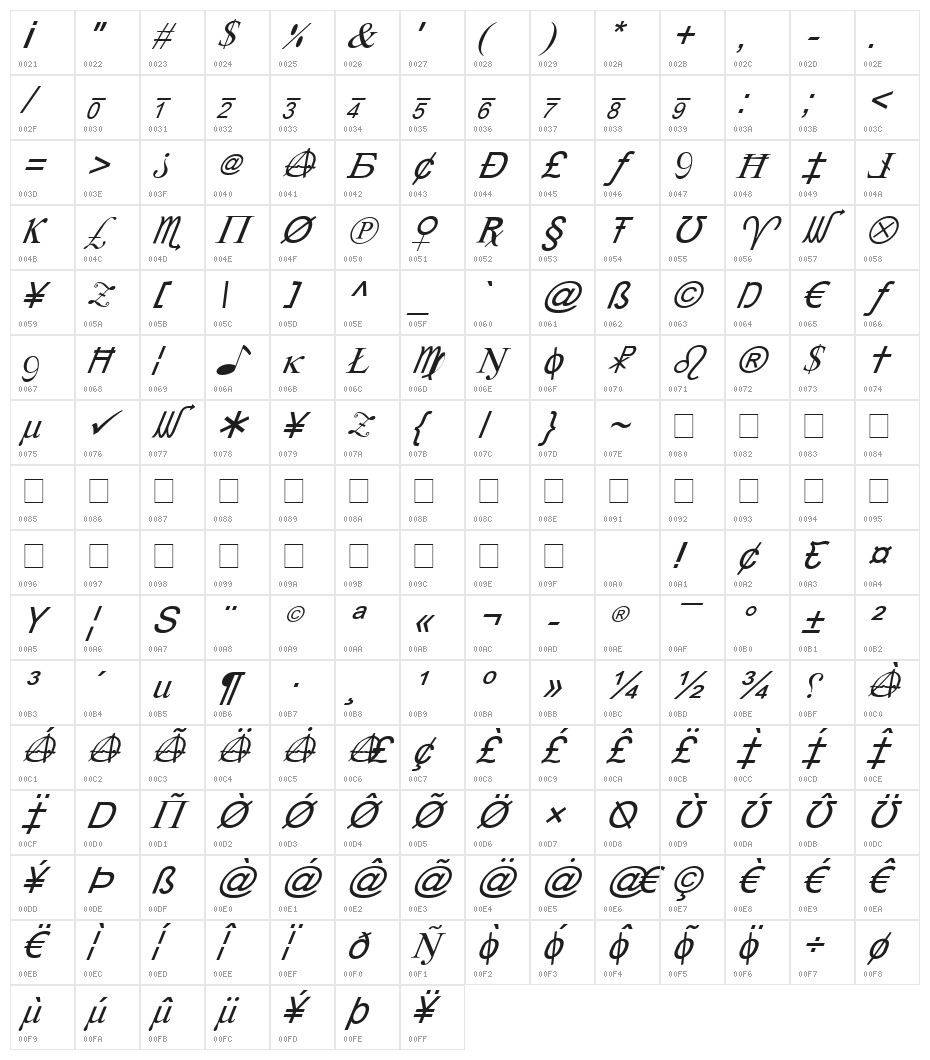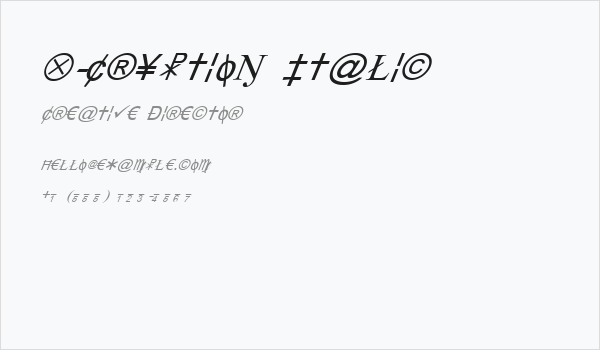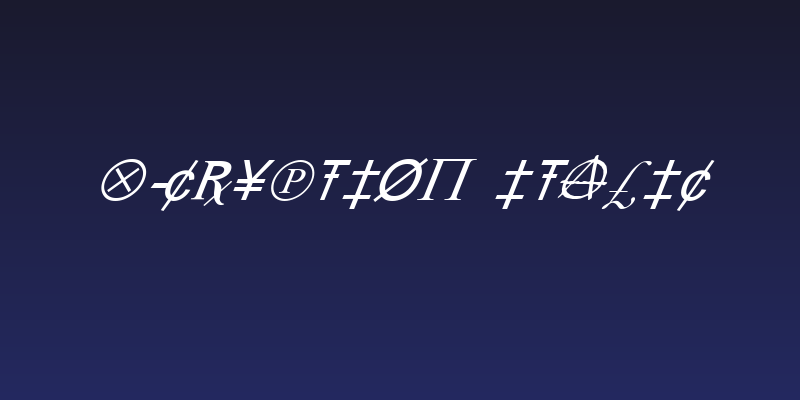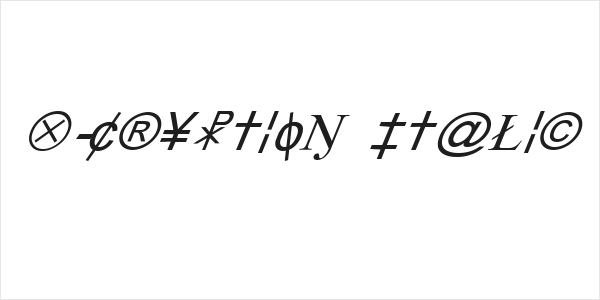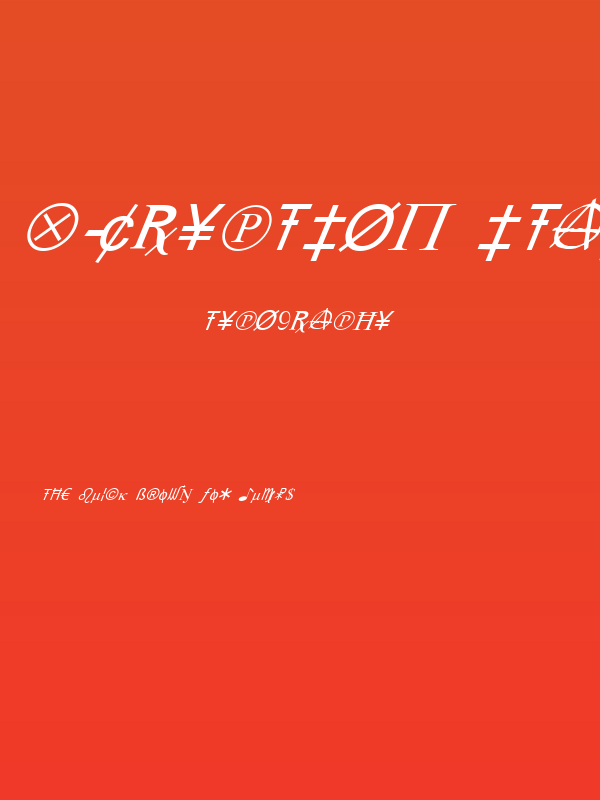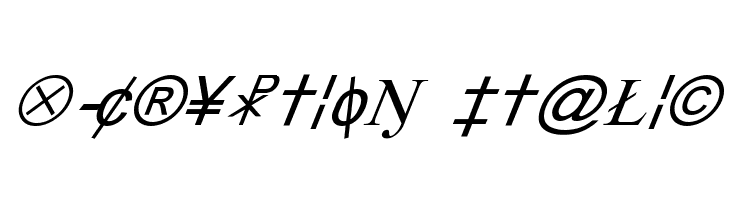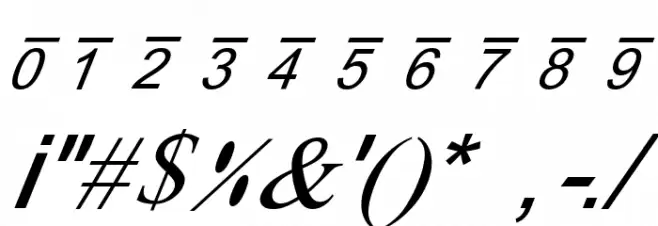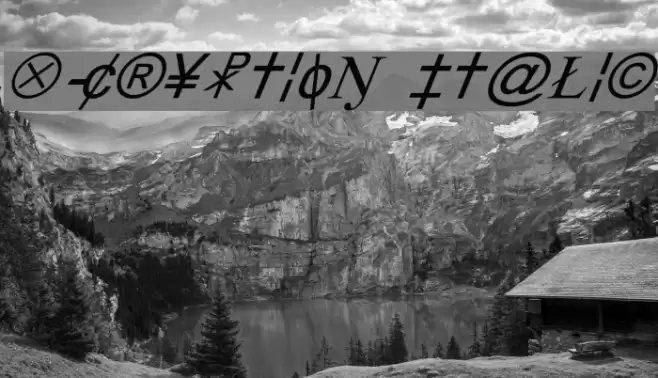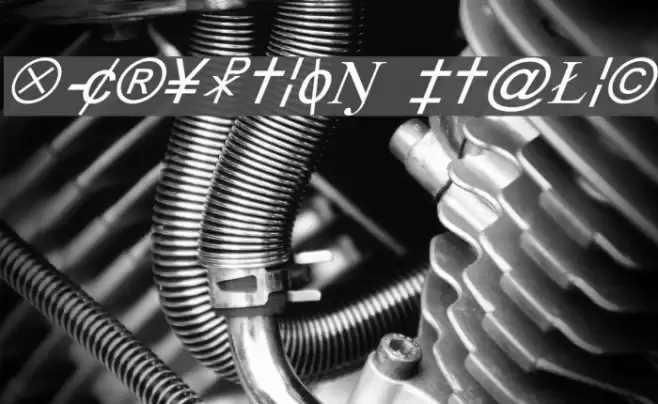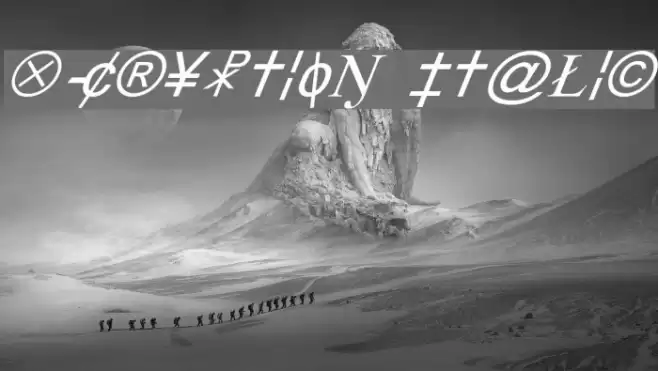
X-Cryption Italic Font
| Proyectos propuestos | Ideal for creative projects such as album covers, posters, branding for edgy or alternative products, and artistic event invitations. |